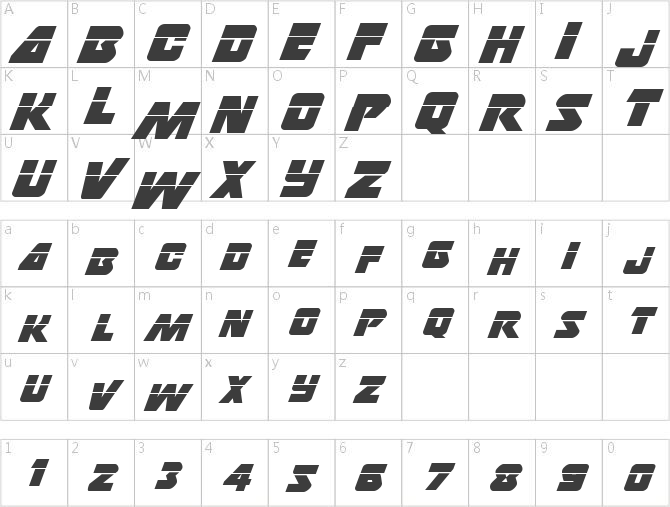
thunderstrikelaser 详情页
字体名称: thunder
thunderstrikelaser
thunderstrikelaser字体字库是一款让人赏心悦目、百看不厌的英文字体,适合各类广告和产品包装设计应用,字体大小0.03MB,格式为ttf字体,上传用户是/zyj【GF】,作者/版权方为未知